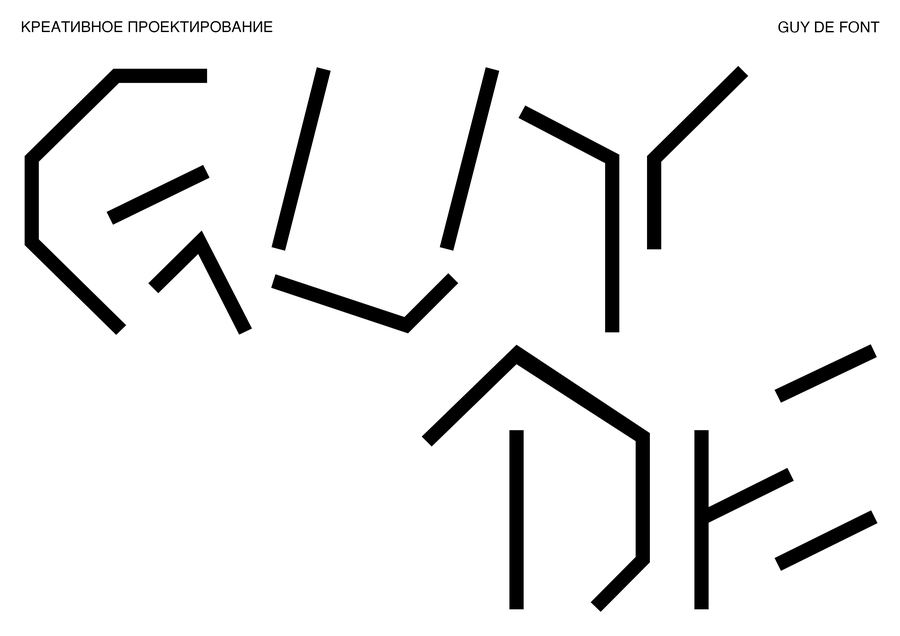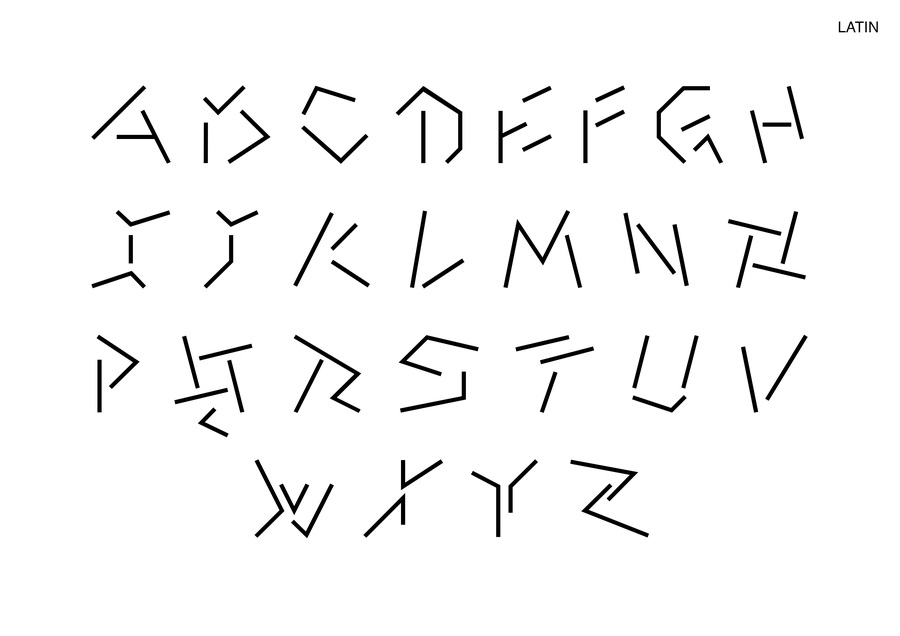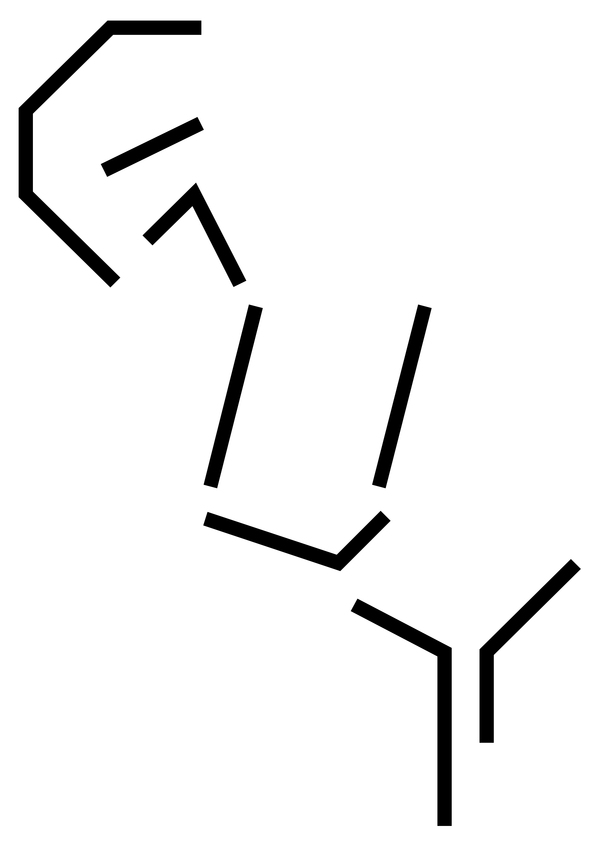
Шрифт «Guy De Font» основан на методе шифрования художником текста, но разработан с акцентом на читаемость при сохранении визуального когда работ Guy De Cointet